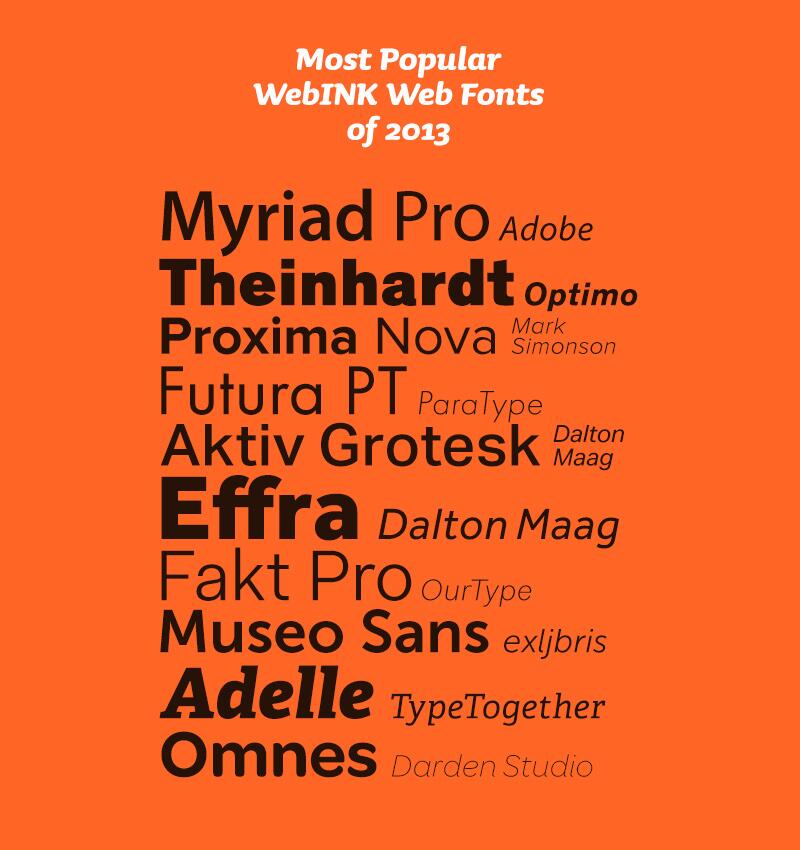
Споры веб-дизайна: действительно ли нужно использовать шрифты без засечек?
Очень долго существовала теория о том, что шрифты с засечками для печатных проектов, а без засечек — для дизайна веб-сайтов. Но с появлением экранов с широким разрешением и большими возможностями печати, это правило больше и не правило вовсе.
Предпочитаете ли вы шрифты с засечками, или без них (а может комбинацию из двух), основной задачей при выборе шрифтов для цифрового дизайна прежде всего должна быть читаемость и разборчивость.
Все просто, вам надо выбрать шрифт, формы которого легко читаются на экране. Частично это связано с тем, где он используется. Например, размер и размещение текста, а затем уже стиль шрифта, который вы выбираете.
Когда употреблять шрифты без засечек
Наверняка многим из вас не понравился этот заголовок. Вы то точно уверены, что такой шрифт идеален для веб-сайтов. И это было правдой несколько лет назад.
Хотя все еще есть случаи, когда Sans Serif нужен:
- для дисплеев с низким разрешением;
- в случаях когда читатели — дети;
при большом количестве цветов или не контрастных паттернах;- когда текст маленький или узкий.
Поприветствуйте экраны с широким разрешением
Что сильнее всего разрушает миф об использовании шрифта без засечек в веб-дизайне так это появление экранов с высокой четкостью. Больше точек на один дюйм экрана делает четче все, в том числе и типографику.
Подумайте об этом вот в каком ключе. Книги на многих электронных носителях загружаются со шрифтами с засечками. И их совершенно легко читать. Потому что разрешение экрана достаточно резкое для обработки линий и штрихов в таком шрифте.
Уже в начале 2012 года, Якоб Нильсен из Nielsen Norman Group, которые фокусируются на исследовании и улучшении UX, отметил, что экраны с хорошим качеством меняют общий вид принципов типографики в веб-дизайне. Вот вывод из этого исследования:
«Старый принцип юзабилити для интернет-типографики был прост: придерживаться шрифтов без засечек. Поскольку компьютерные экраны паршиво отображали засечки, использование таких шрифтов в тексте приводила к размытым буквам.
… К сожалению, новый принцип не такой четкий, как старый. Исследование читаемости не позволяет сделать окончательный вывод на счет того, действительно ли шрифты без засечек лучше, чем с засечками?. … Почти все крупные печатные газеты, журналы и книги используют шрифты с засечками, так люди привыкли читать длинные тексты в их стиле. Однако, основываясь на данных исследования, разница в чтении шрифтов с засечками и без, не так и велика. А значит нет особых преимуществ в пользу использования одного или другого, так что вы можете выбирать по иному принципу — например, в зависимости от брендинга, настроения или определенной концепции типографского стиля.».
Но сейчас мы начинаем наблюдать, что все больше дизайнеров используют эту идею.
Читаемость
Читаемость — это возможность легко прочитать написанное. Есть множество факторов, которые ей способствуют, включая интересный контент (или нет), и как все это выглядит, когда собирается в единый текст.
В общем, вы можете надолго залипнуть, когда дело касается эстетики и удобства чтения. Если вы можете сказать, что сайт пытается донести с первого взгляда — он читаемый.
Разборчивость
Разборчивость относится к качеству написания, и ясности написанного текста. Хорошую типографику должно быть легко читать. Выбор шрифта зависит от разборчивости. (Подумайте о почерках, и какой из них вы назовете разборчивым, а какой нет. Тоже самое с цифровыми буквами).
Когда дело касается разборчивости, каждая буква должна четко отличаться от других. Учитывая все факторы, включите все, от фактической формы обычного и жирного написания, маленьких и заглавных букв, расстояние между ними, использование засечек или другого орнамента.
Одно из основных правил читаемости — шрифты должны быть более круглые, отчетливые, с большой Х-высотой, адекватным и последовательным расстоянием между буквами, и простым характером.
Советы по выбору шрифтов
Вы все еще зациклены на применении шрифта без засечек для вашего следующего проекта? Вот несколько советов для выбора лучшего варианта без засечек.
- Выбирайте шрифты, буквы которого четко разделены: отойдите на шаг от монитора и посмотрите на шрифт, который выбрали. Вы легко можете разобрать отдельные буквы? Выбор шрифта с хорошим расстоянием, делает его легко читаемым на любом размере экрана, особенно на очень маленьких, или, наоборот, очень больших.
- Остановите свой выбор на средней насыщенности: шрифты с обычной шириной штриха. Слишком тонкие или слишком толстые шрифты (вспомните споры на счет iOS 7 Apple) могут сложно читаться. Для основного текста выбирайте что-то среднее между средней и универсальной шириной штриха.
Применение толстых и тонких штрихов может вызвать некоторые проблемы. - Посмотрите на качество шрифта: скачивание любого старого шрифта для веба, может не дать вам того результата, который нужен для проектов. Придерживайтесь шрифтов авторитетных авторов. И внимательно изучите его на экране. Вы можете увеличить его в 200 — 500 раз от фактического размера и при этом получить хорошее изображение? Благодаря таким ресурсам, как Adobe Typekit и Google Fonts, существует большое количество доступных шрифтов для интернета, которые помогут создать хорошее впечатление вашему проекту. И хотя вы не всегда можете сочетать шрифты для печати и цифровых проектов, ищите тот стиль, который подчеркнет вид и восприятие вашего бренда.
В случае Typekit дизайнер покупает подписку на библиотеку шрифтов. Затем Typekit предоставит дизайнеру фрагмент кода JavaScript или CSS для использования на страницах HTML. Когда пользователь посещает сайт, код запрашивает шрифты из системы Typekit; если запрос исходит от сайта, зарегистрированного в Typekit, шрифты динамически вставляются на страницу.Все беспорядочные технические детали, такие как обслуживание правильного формата для браузера посетителя, автоматически обрабатываются за кулисами. Typekit делится прибылью от подписки с владельцами шрифтов. Typekit защищает шрифты, изменяя их таким образом, чтобы сохранить их визуальную целостность, но не позволяет их установить в операционной системе. В результате многочисленные литейные предприятия сделали сотни высококачественных шрифтов доступными с помощью этой службы.